人间逢小年,所求都如愿。今天是农历腊月廿三,北方传统习俗中的小年,除了扫尘土、祭灶王,忙年备新办年货可是重中之重。就咱设计师来说,少不了备一份“字”带年味儿的精美字体清单,好字写好年,这波氛围感拿捏了!
方正全福体
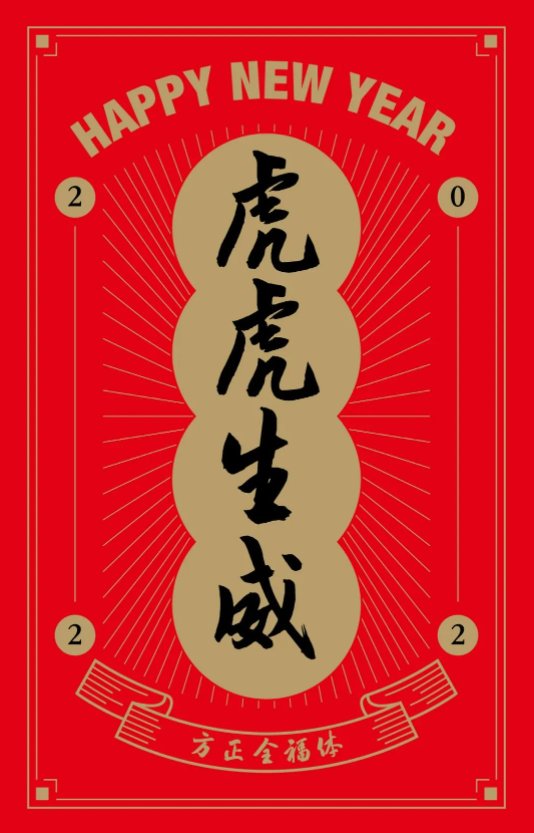
设计师:仇寅
方正全福体是福建省文化和旅游厅与方正字库联合推出首款区域性定制字体,也是国内首款由省级政府文旅管理部门定制的字体。“全福体”由方正书法专家仇寅书写设计而成,受福建山水人文浸润三十多年的仇寅,在书写设计过程中,融合了宋代“尚意”书风的格调,并考虑字库的易识性、通用性,进行了多次书写尝试及优化调整,最终完稿的“全福体”给人以文雅、厚重、大气之感,雅俗共赏。“全福体”将福建独特的特征和记忆点融入字体的一笔一画间,可应用于各类传播媒介和公共空间,在城市形象宣传和推广方面都将产生微妙却不可小觑的影响力。
方正侠客体
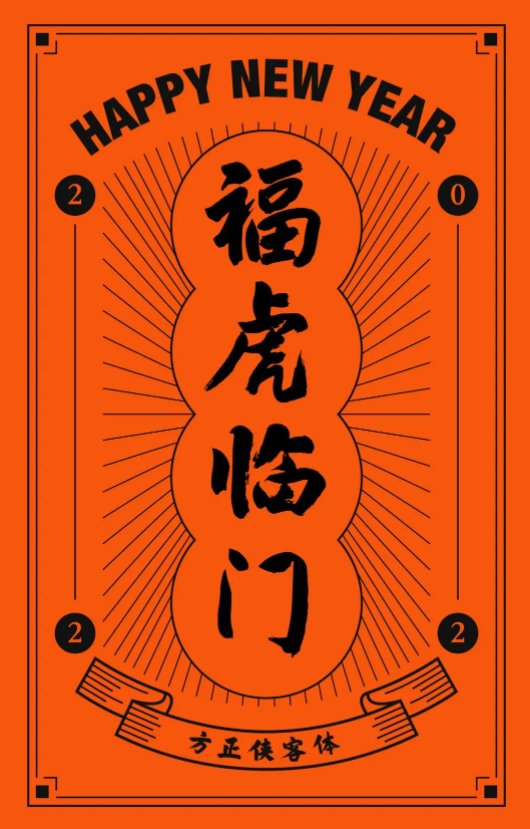
设计师:张弥迪
方正侠客体的创作源自设计《评书聂隐娘》出版物,写字如挥剑,讲究轻重缓急,当时希望用这种斩钉截铁的率性书写来呈现侠客的潇洒与果敢。 师法古代经典碑帖,比如颜真卿、张即之、朱熹等名家作品,字形以行楷为基准,尽可能保留笔画的丰富性,比如粗细变化、相同偏旁部首的变化以及飞白的效果等。作者希望创作一种既符合传统书法的笔法与结构,又能具有视觉设计张力的书法标题字体。主要适用于广告、包装、影视剧的标题等。
方正苏轼行书
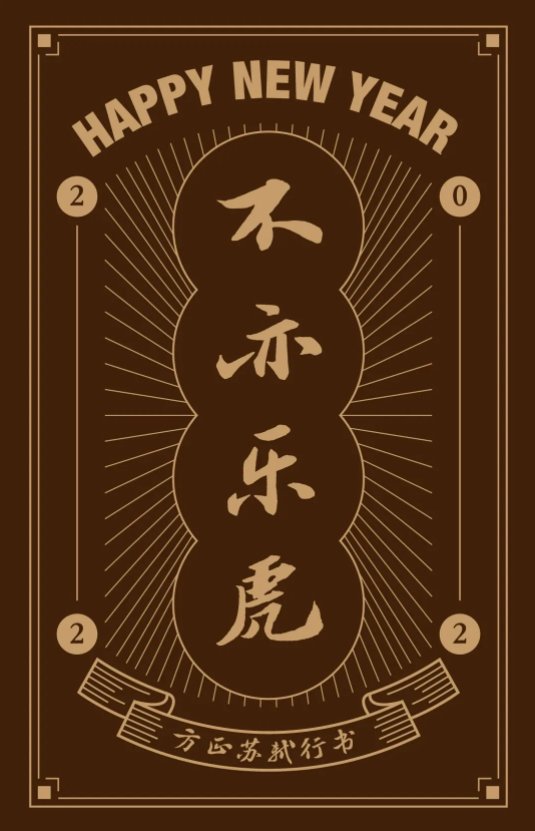
设计师:仇寅
审稿专家:吴行、欧阳荷庚
关于书法家:苏轼(1037-1101),北宋文学家、书画家。字子瞻,号东坡居士,眉州眉山(今属四川)人。其文汪洋恣意,明白畅达,为唐宋八大家之一。其诗清新豪健,善用夸张比喻,在艺术表现方面独具风格。擅长行书、楷书,取法李邕、徐浩、颜真卿、杨凝式,而能自创新意。用笔丰腴跌宕,有天真烂漫之趣。存世书迹有《答谢民师论文帖》、《祭黄幾道文》、《前赤壁赋》、《黄州寒食诗帖》等。
字体特征:方正苏轼行书以苏轼字帖(信札、手卷)、刻帖为开发依据。笔法丰腴、结字扁平,横轻竖重、撇捺舒展,随形变化、错落有致,体现了自然率真、拙朴敦厚的深蕴。
方正爨宝子碑楷书
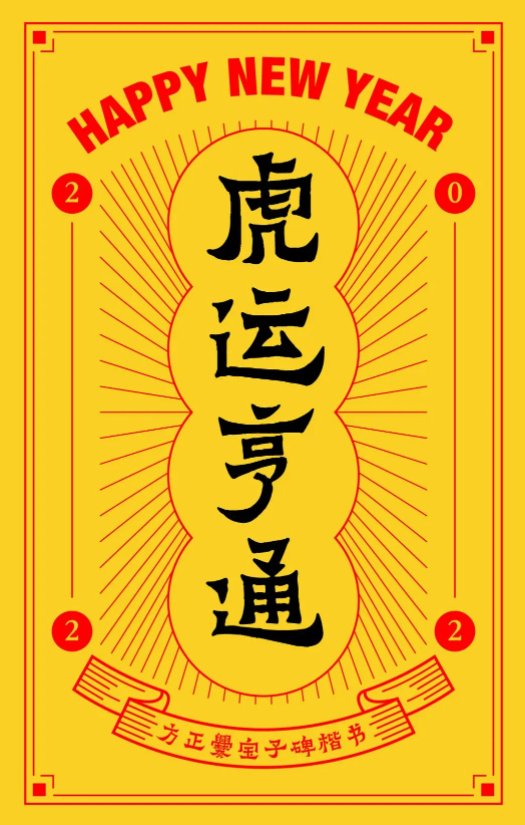
设计师:苏新诗、汪文
审稿专家:郭伟
关于爨宝子碑:义熙元年(公元405 年,此时已改年号为义煕,或因边陲闭塞,故书碑人仍依旧年号写作“大亨四年”)立。清乾隆四十三年(1778 年)在云南曲靖南七十里扬旗田出土,道光十五年(1835 年)《云南通志》始著录,咸丰时移置城中武侯祠。书体在隶楷之间,可见文字由隶书演变为正书过程中的一种风格。
字体特征:方正爨宝子碑楷书以《爨宝子碑》为字形开发依据。朴茂古厚,大巧若拙,率真硬朗,气魄雄强,奇姿尽现,浑然天成。体势情趣、情态均在隶楷之间。
方正字迹-龙吟体
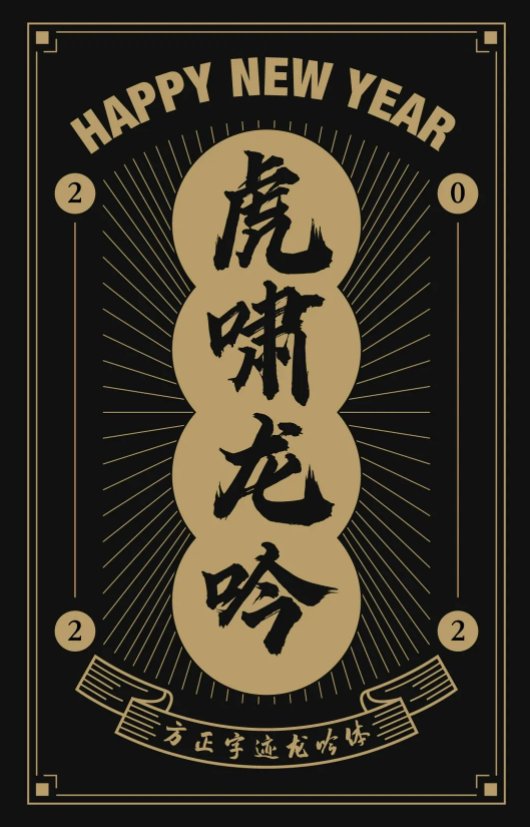
设计师:曹基殿
方正字迹-龙吟体笔画刚硬锐利,笔触狂放,字形浑厚洒脱,且结构多变。不仅适用于横向、纵向的排版,还方便了字与字之间的穿插。在继承传统的同时又融入当今商业化的应用,适合于电影海报、包装、品牌名称、各类商业海报、户外广告标题等。
可口可乐在乎体
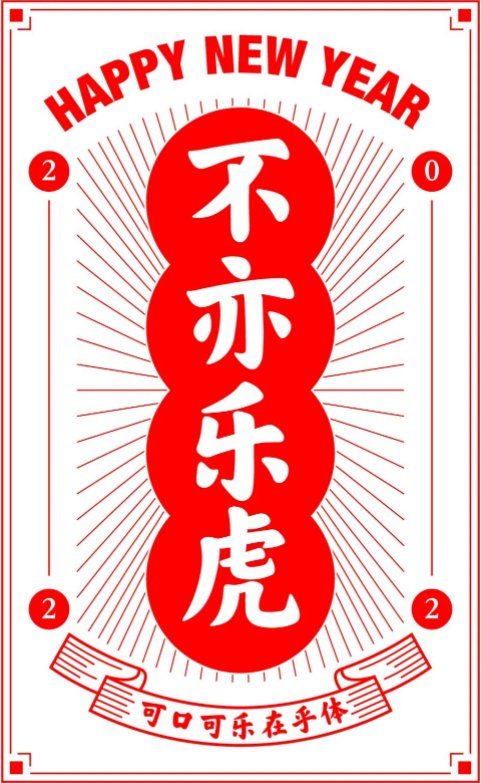
设计师:可口可乐中国、好字在、方正字库
全球知名品牌可口可乐公司在中国市场深耕四十多年,在这里经营、生活、成长,也深受中华文化和精神启发。为了致敬这份文化共鸣,可口可乐中国以重返中国早期的老商标字体为灵感原点,邀请汉字文化推广机构好字在和方正字库一起,创造了一套字体,命名为“可口可乐在乎体”。作为一款全新的品牌定制字体,“在乎体”从情怀出发,用具象的设计方法,借由每一笔一划,表达中国人对“在乎”的理解和诠释——圆融、力量、担当、从容、进取,希望在数字化时代,为大家提供一种有人情味的字体选择。用在乎体,写在乎的事,给在乎的人。
方正白舟武骨体
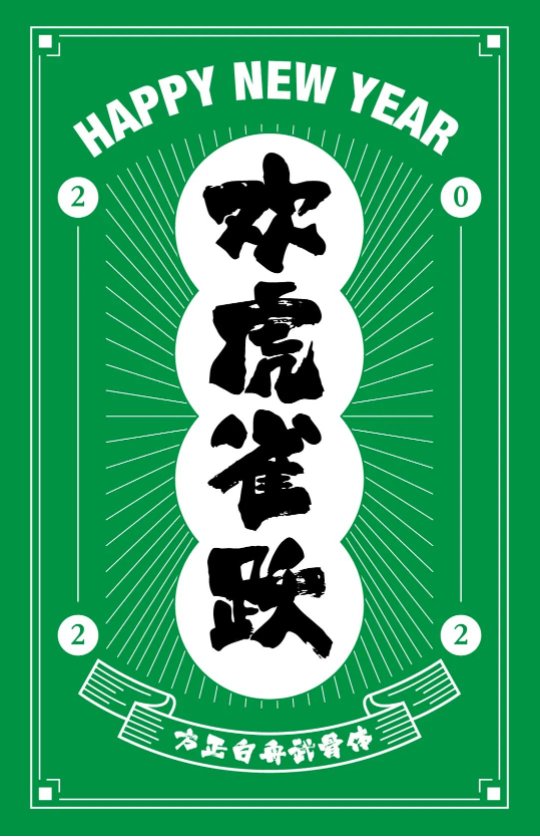
方正白舟武骨体的个性沉默、安静、天真、狂野、憨直、粗暴、倔强,代表男性的形象。这是一款中宫紧凑的方形字体,笔画粗壮有力,乍看之下像是一个不太成熟的未成年人,同时又呈现出一种稳健自若的精神面貌。运用枯笔书写出来的白舟武骨飞白鲜明、坚固厚实,给观者以一种倔强粗犷的印象,适用于大字招牌,和传统文化类的标题、短语这种需要视觉具有冲击感的场景。